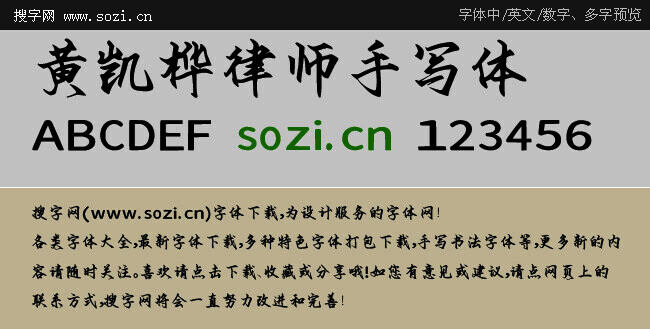
黃凱樺律師手寫體
搜字網(wǎng)提供一款黃凱樺律師手寫體中文書法字體下載,黃凱樺律師手寫體是一套根據(jù)簡體中文漢字編碼國家標準(GB2312編碼)設計的字體,并在此基礎上一共設計了6769個簡體漢字,為一款原創(chuàng)字體,具有其獨特的字形風格。這套字體面向全社會(包括企業(yè)商用)永久免費開放使用。適合圖書設計、包裝設計、海報設計等應用。
- 風格類別: 手寫書法體